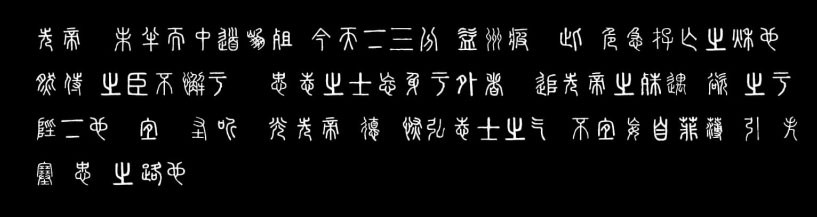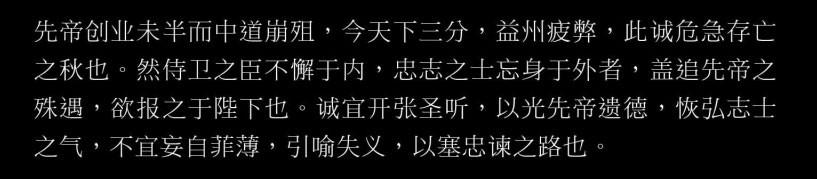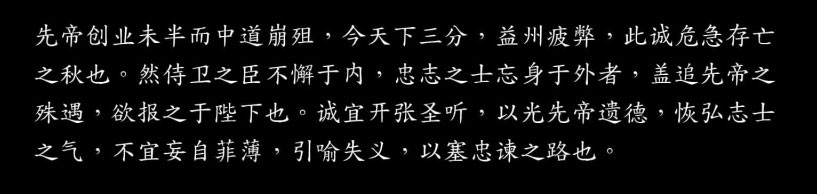
全字库正宋体、正楷体和说文解字,免费可商用中文字体
全字库正楷体(TW-Kai)来自中国台湾为了统一资料交换使用的内码而制定的标准字元编码方案,标准交换码让不同内码也可以沟通交换内容;全字库正楷体就来源于该计划推出的全字库。中国台湾的全字库有提供两款免费、可商用的中文字体可供下载。这两款字体分别是全字库正楷体和全字库正宋体。
全字库正宋体
全字库宋体就像是微软的新细明体,为一般大众常见的字体,非常适合用在中文与英文。
全字库正楷体
全字库正楷体就像是微软的标楷体,适合用在较为正式的中文书面报告或是公文。
全字库说文解字
全字库说文解字体采用小篆的风格,并将书法感和设计融为一体,笔画匀圆,并有横竖行笔,形体趋于方正。由于说文解字原文与现行之Unicode编码并无一完整的对应,因此无法将所有的字形收录于本字体内。以致于会有部分字码无法显示出正确的字形!目前收录于本字体内的字数共6721个字。以 “全字库” 冠名的字体由中国台湾地区的行政机关开发并维护。